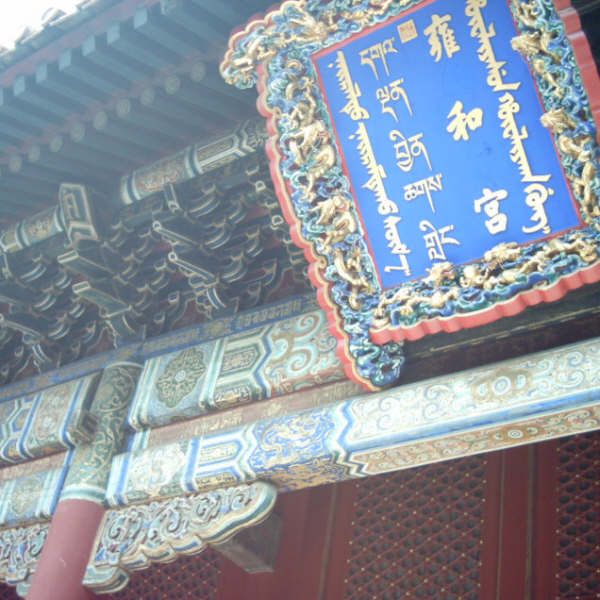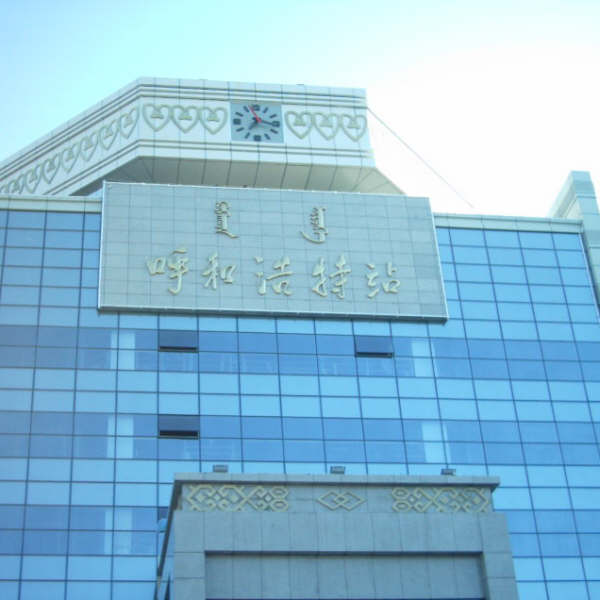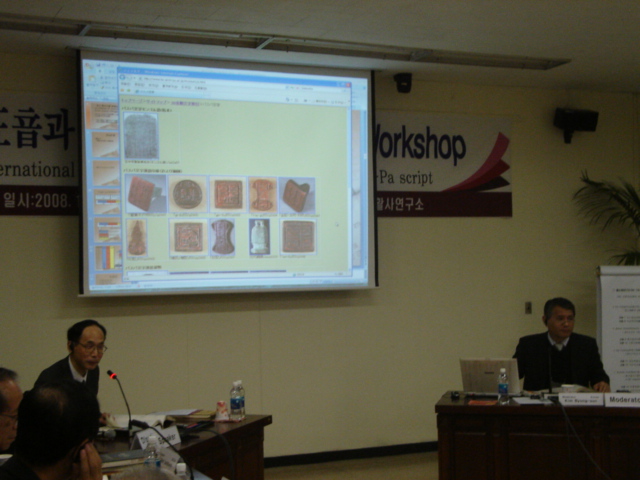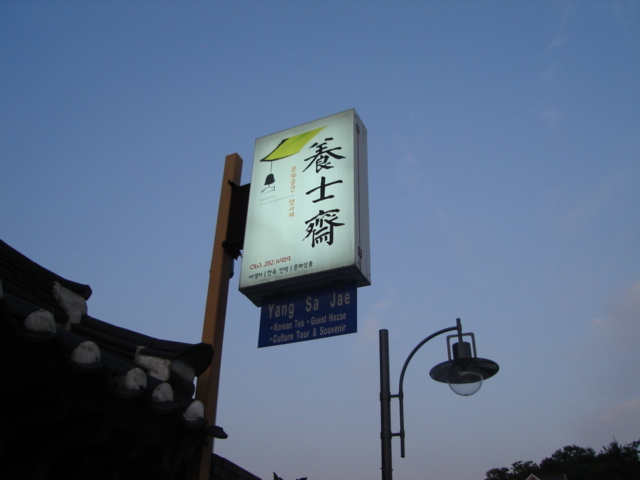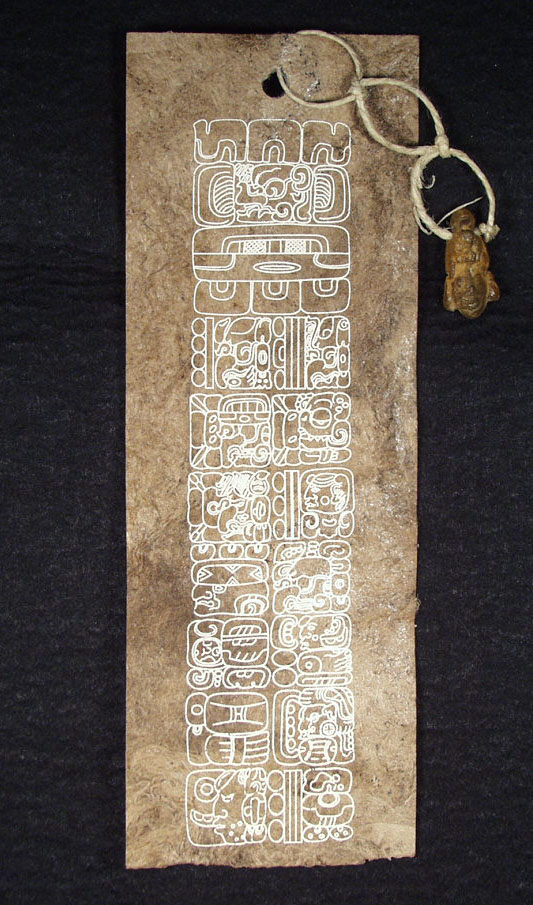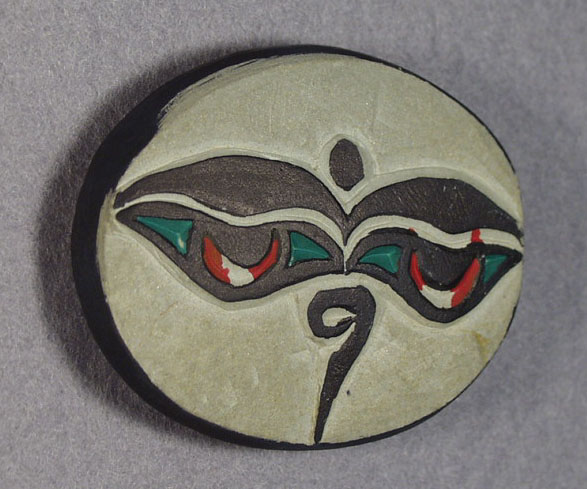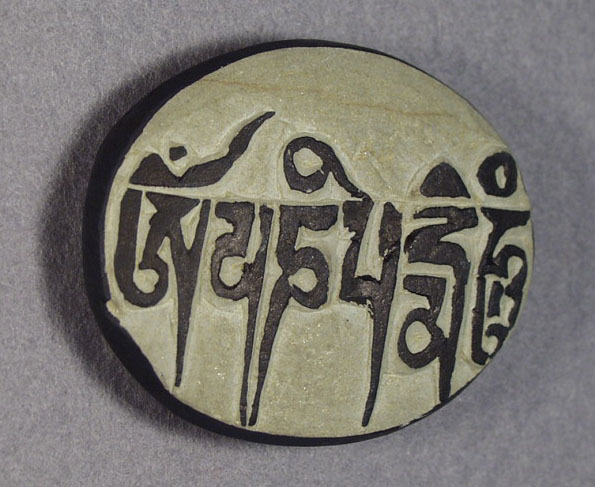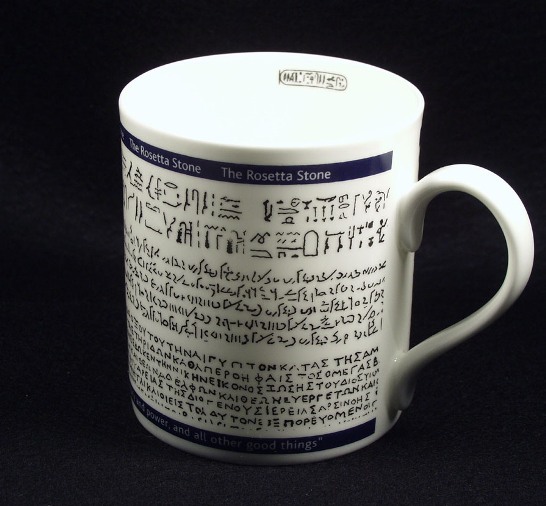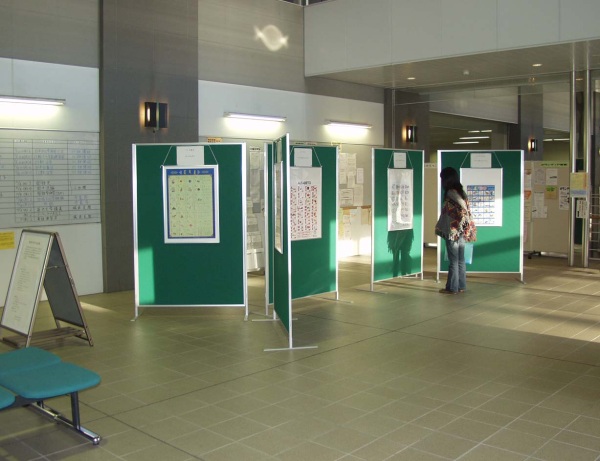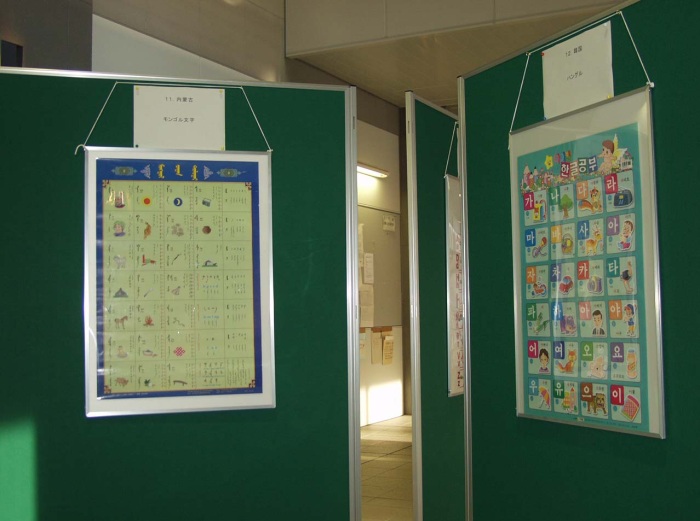
養士斎に泊まる 9月12日(土)、13日(日)の両日、韓国・全州の又石大学校で開催された「訳学書学会創立総会及び学術発表会」に出席してきた。僕としては、発表の準備よりもこの学会に『訳学書文献目録』(ソウル:博文社,2009年9月)の出版を間に合わせるまでがとにかく大変たったので、全州にたどり着いた時にはすでに燃え尽き症候群のような状態だった。この間の経緯については遠藤光暁先生の「先進国としての韓国―中国語学研究を通して見る」(『東方』346号,2009年12月)に詳しい。 会議では初代会長となられた鄭光先生(高麗大学校名誉教授)を始め韓国側の諸先生から連日歓待を受け、また研究上の交流も非常に実り多いものだったが、滞在最後の日に遠藤先生・更科慎一氏とともに「養士斎」(ヤンサジェ)という伝統的韓国住居に泊まったことがとても印象に残っているので、今回はそれを写真で紹介しよう。
→他の写真へ 養士斎は伝統的な家屋と街並が保存されている「全州韓屋村」の一角にある。詩人・朝鮮語学者として名高い李秉岐氏(1891-1968)の旧居で、氏が1950年代に全北大学校の文理大学長を務めていた時の住まいであるという。現在は民宿となり一般客も泊まれるのだそうで、今回はソウル大学校に留学中の杉山豊さんが予約を取って下さった。 朝鮮語学に明るくない僕は、最初李秉岐先生の旧居と聞いてもピンとこなかったのだが、その号が「カラム」であると聞いて、おお、あの「カラム文庫」のカラムか! と一気に気分が盛り上がった。ソウル大学校奎章閣のカラム文庫は、訳学書の所蔵機関として目録にさんざん出てきたからである。 中に入ってみると、そこかしこに見られる素朴な山里の雰囲気が「燃え尽き」の身には実に心地よかった。荷物を降ろし、皆で少し周りを散歩したあと、夕食には全州名物のビビンバを食べ、近くの伝統茶室でお茶を一服してから養士斎に戻った。 泊まったのは通常のオンドル部屋だから、当然部屋は狭く布団は薄く床は固い。加えて僕は寝つきが悪いので、いつもはラジオかCDでもつけないとなかなか眠れないのだが、この日はそんなことが全く気にならず、あたかも全身を良い「気」に包まれているような感じで深い眠りについた。 翌日は早々にソウルに向けて起たなければならなかったので、あまりゆっくりできなかったのが何とも残念で、機会があればぜひまた訪れてみたいと思っている。カラム先生にあやかって、あの良い「気」が頭の方にも効いているとよいのだけれど。 [2009.12.15 竹越孝] |
文字と意匠―(5)ロゼッタ・ストーンの文字をあしらったマグカップ 文字本来の用途から離れてデザインとして描かれた文字がある。いろいろなものがあるが、 しばらくは陶磁器に書かれた文字を見ることにしたい。 このマグカップは大英博物館で購入したものという。過日、知人より土産として当館にご 寄贈いただいた。おそらく、当サイトの“いろいろな話”をご覧のうえで、お気遣いいただいたの であろう。嬉しい限りである。
ただし、マグカップにプリントされた3種の文字が、内容において対応しているわけではない。マグカップのヒエロ グリフ(2行)は、ロゼッタ・ストーンのヒエログリフ部分の最下部の2行から採ったものである。デモティック(5行)は最上部 の5行から、ギリシア文字(6行)は最上部の6行から採ったものである。 ここで、マグカップの写真をもう一度ご覧いただきたい。カップの内側に、楕円の枠(カルトゥーシュと称す。永遠を 象徴する結んだ縄の枠)に囲まれた文字がある。これはロゼッタ・ストーンのヒエログリフ部分の最下段から採ったもので、 プトレマイオス5世の名である。ヒエログリフで刻されている。ギリシア文字ギリシア語文の方にもプトレマイオスの名は 登場する。解読者シャンポリオンは、このような固有名の対応を契機として、エジプト象形文字の解読を成功に導き、一躍 時代の寵児となったというわけである。 さて、“文字と意匠”という面から、このマグカップみた場合、どういうことになるのであろうか。マグカップの作り手は、 言うまでも無く、文字による情報伝達は意図していない。博物館の顔であるロゼッタ・ストーンの文字をあしらって来館の記念品とし、 販売促進を考えたという面はあるであろう。あるいは博物館の宣伝にもなると考えたかもしれない。 カップの利用者のほうはどうであろうか。いま、故郷の我が老母がカップを手にした図を想像しているのであるが、文字意匠 はそれほど美しいものではないから、これに関心は示さず、“落書きのない方のカップをくれろ”と心の中でつぶやくに違いない。 もっとも、最近はヒエログリフを目にする機会も少なくないから、この文字意匠によって古代エジプトを想起する方もおられる であろう。ロゼッタ・ストーンの所有国イギリスや解読者シャンポリオンの母国フランスの人々であれば、更に別の感慨を抱くの かもしれないが、そのあたりのことは確かめたことがない。しかしなんといっても、大英博物館の土産であること、ロゼッタ・ストーン を模したものであることに“関心を持っている”人の手の中で、このマグカップの文字は文字意匠としての効用を最大限に発揮す ることだけは間違いない。現にいま手の中で輝いている。 [2009.11.17 吉池孝一] |
おみやげ 先月、友人からお土産を何点か頂いた。ベルギーで開かれた学会に出席したということで、まずはオランダ語の(オランダ語による)文法書を一冊。私は学生時代にオランダ語の授業には初回に顔を出しただけで、結局履修するのをやめたため、オランダ語の知識はないが、英語とドイツ語の中間的な特徴を示している(ように見える)ので、ただ眺めていても面白い。件の友人もやはりオランダ語は話せないので、ベルギーではドイツ語を使っていたらしい。それでも相手は理解し、英語で答えた(!)ことで無事に意思の疎通がはかられた由。実はベルギーではオランダ語とフランス語以外に、ドイツ語も公用語の一つだということを後に知った。 そして、彼女がパリに立ち寄った際、チベット物産店(?)で入手したという御利益のありそうな石も頂いた。手のひらに収まるサイズのもので、これがその写真。
ついでに、と言って、去年メキシコに行った時に入手したというお土産も頂いた。マヤ文字が記された栞(?)である。 ![]() [2009.10.21 中村雅之] |
京都国立博物館の展示 先日、「シルクロード 文字を辿って」という展示を見に、館員一同で京都に行って来た。日本にいてこれだけの展示を見る機会もめったにないだろう。 今回の展示は、文字資料のみで構成されているのが大きな特徴である。従来「シルクロード」と題した展示では仏像や絵画や種々の器といったモノが中心であったが、今回は文字の記された資料100点以上を展示しており、文字に興味を持つ者にとってこの上なく楽しい展示であった。 ![]() →他の写真へ 100年以上も前に建てられたという京都国立博物館の奇妙な外観にしばし呆然として入り口の入場券売り場に行くと、やたらと大きな看板が出ていた(上の写真)。まずは構内のカフェで簡単な食事を済ませ、それから本館に入った。 今回の展示はほとんどがロシア探検隊の収集物で、展示物の配置は出土地別になっていた。順路に沿って、最初にコータン、クチャ、トルファンなどから収集したカローシュティー文字、ブラーフミー文字、ソグド文字、ウイグル文字などの写本、次に敦煌から収集した大量の漢文文献やチベット文字資料、最後にハラホト出土の西夏文字資料など、いずれも逸品ぞろいで見ていて飽きないものばかりだった。 関連展示として、京都の各地に保管されている国宝・重文級の古写本や版本も十数点あって、中でも原本『玉篇』の古写本の断簡は見応えがあった。 このような充実した文字資料の展示は、1998年に東京で開かれた「法華経とシルクロード」展(東洋哲学研究所主催)以来であろう。その際には、ロシア・東洋学研究所(サンクトペテルブルク)所蔵の仏教文献が公開され、14の言語による47点の展示があった。今回の京都の展示では、言語と文字の種類では遠く及ばないが、何と言っても140点余りの資料をそろえた点が評価できる。ちなみに、今回展示されたカローシュティー文字「法句経」は前回の東京での展示でも見た(はずの)もので、この資料の来日は2度目ということになる。 また、今回はロシア探検隊の収集物をまとめて展示したこともあって、クレメンツ、オルデンブルク、コズロフ、ペトロフスキーという、探検隊に関わった人たちの肖像や解説も備わっていて、ロシアの中央アジア学を総合的にとらえるいい機会になった。 [2009.9.16 中村雅之] |
文字と意匠―(4)“いろは”の花器 文字本来の用途から離れてデザインとして描かれた文字がある。いろいろなものがあるが、しばらくは陶磁器に書かれた文字を見ることにしたい。 これは、“いろは歌”四十七文字に“ん”を加えた48文字の“いろは”の花器である。小さな火鉢くらいの寸法で、見てのとおり、全面に筆で平仮名が書かれている。この花器(安物の信楽焼)であるが、近所の行きつけの喫茶店で購入した。実はこの喫茶店、陶磁器店も兼ねている。陳列棚に並んでいたものを見そめて購入したというわけである。しばらくの間、研究室の片隅で眠っていたが、今回無事にデビューとなった。
文字と意匠―(3)漢文の陶製枕 文字本来の用途から離れてデザインとして描かれた文字がある。いろいろなものがあるが、 しばらくは陶磁器に書かれた文字を見ることにしたい。 ![]()
群鳥冷栖霜在木 (群鳥 冷栖シ、霜 木ニ在リ) 孤?寒叫月懸山 (孤猿 寒叫シ、月 山ニ懸ル) “対聯”と呼ばれる対句である。その意味するところは“群れなす鳥が寒々と木の枝に止ま っており、その木には霜が降りている。遠く孤猿の寂しげな叫び声が聞こえる。見ると山の上 には月が懸かっている。”というところであろうか。静寂な雰囲気であることだけは確かである。 枕の作者は、“寝る前にこの対聯を見て穏やかな心持で眠りに就いてもらいたい”との願いを 込めて作ったのであろうか。或いは、よく眠れるようにとの“おまじない”であろうか。もっとも、 この手のものは、作者の意図と、日常枕を利用する人の思いが一致するとはかぎらない。あんがい、 ただの飾りとして気にも留めないというのが、ふつうの在り方なのかもしれない。 なお、広州の南越王墓博物館の一角で、さまざまな枕が収集展示されているという。機会があれば 一度のぞいてみたいと思っている。[2009.5.13 吉池孝一] |
文字と意匠―(2)ハングルのマグカップ 文字本来の用途から離れてデザインとして描かれた文字がある。いろいろなものがあるが、しばらくは陶磁器に書かれた文字を見ることにしたい。 さて、昨年のことであるが、友人宅におじゃましたおり、ハングルがあしらわれたマグカップをみた。聞くと、韓国のスターバックスで売っているという。その後、韓国に行く機会があったので、ソウル市内の、くだんのコーヒーショップで買い求めたのが、この磁器製のカップである。 ![]() この韓国語(李朝時代の言葉)を現代の市民がどれほど読めるものか、門外漢のわたしには分からないが、内容自体は周知のものなのであろう。民族の誇りともいうべきハングル創製の由来が書かれたこの文は単なる意匠ではなさそうだ、ということは想像できるのであるが、それ以上のことはなんとも言いようがない。 [2009.4.15 吉池孝一] |
文字と意匠―(1)京都弁の湯飲み茶碗 文字本来の用途から離れてデザインとして描かれた文字がある。いろいろなものがあるが、 しばらくは陶磁器に書かれた文字を見ることにしたい。なぜ陶磁器なのか、理由はない。 ![]() さて、対訳というのは或る言語を他の言語で「説明する」ということであるから、この文字群は 意匠であるとともに、情報を伝えるという文字本来の働きもじゅうぶんに示している。 陶磁器の意匠としては珍しいほうである。それは、日常品としてではなく、修学旅行の学生 や一般の旅行者を目当てに土産物として作られたためであろう。「京都弁と共通語の茶碗」、 土産として話の種になりそうである。 このようなばあい、湯飲み茶碗本体が主役なのではなく、主役は意匠の方なのであろう。 主客逆転ということであるならば、これらの文字は単なる意匠ではないかもしれない。 なお、京都弁は平仮名のみで綴られ、対応する共通語は平仮名と漢字で綴られている。方言は 漢字表記の対象にならない音声言語ということである。 [2009.3.13 吉池孝一] |
中国の民族文字資料(3) 今回は中華民族園です。中華民族園は、北京中心部の北側、環状の幹線道路・三環路を出るものの、地下鉄、バス路線では案外便利な位置にあります。すぐお隣はオリンピックセンター、園内からも「鳥の巣」やスタジアムがよく見えます。 ここは、国内の各少数民族の居住建築や展示を集めた、犬山市のリトルワールドのようなテーマパークです。さすがは中国で、テーマパークとはいえ、国内の全民族を集結させた園内は気が遠くなるほど広く、とても一日では回り切れませんでした。見ることのできた、少数民族の文字をいくつかご紹介します。 ![]() →他の写真へ 山間部に住む民族が多いためか、ほとんどのエリアが、なぜあんなところにというような急傾斜の丘の上に作られており、真夏の炎天下、延々階段を上っては下りの繰り返しでかなりの体力を必要とする園内でした。でも、国内旅行せずして、一日でいろいろな民族の文化の一端だけでも触れることができるのは(斜面の上り下りも現地疑似体験の一環?)なかなか悪くなかったと思います。あいにく行き当たりませんでしたが、指定の時間に行けば、各民族のダンスや歌の上演を楽しむこともできます。展示を見るだけでなく、歌や話で少数民族の言葉を体験できれば、暑さも少しは和らいだかもしれません。 [2009.2.13榊原真理子] |
国際ワークショップ参加記B〜蔵書閣のこと〜 今回のワークショップが行われた韓国学中央研究院の中で、ぜひとも行ってみたかったのが蔵書閣だった。ここはソウル大学校奎章閣と並び称される古典籍の所蔵機関で、いわゆる中国語学の朝鮮資料も豊富に収蔵されている。 蔵書閣のある場所を聞いてみると、ワークショップ会場のすぐ裏手だということだったので、一日目の昼食を食べてから遠藤先生はじめ数人で訪れることになった。僕は午前中最後の発表のディスカッサントということで、本当はそれが終ってすっきりした気持ちで行けるはずだったのだが、日程が押していたため午後の最初に討論を行うことになり、いま一つ気勢が上がらなかった。 蔵書閣は近代的な外見だが古風な感じもする建物で、日本の国立公文書館に似ているという印象を持った。僕は中に入っただけで満たされた気持ちになり、それ以上は期待していなかったのだが、せっかくだから何か請求してみたらどうですか、との遠藤先生のご示唆もあって、20世紀初の写本資料『你呢貴姓』を探してもらうことにした。何せ、僕は今年のゼミで数人の学生さんとともにこれを読んでいるのだ。なお、僕に司書の人とやりとりするだけの会話力はないので、折から留学中の杉山さんと野村さんが通訳を務めて下さった。 ![]() →他の写真へ ところが、コンピューターで検索しても一向に引っかからないという。司書の方があれこれ調べて下さった結果、『蔵書閣ハングル資料解題』にたどり着き、確かに所蔵されていることがわかった。「你呢」は韓国では僻字だし、何か条件に問題があるのだろうということで、司書の方は「貴姓」で引っかかるようにその場で(!)ウェブページの検索条件を変更してくれた。なお、帰国後調べてみたら、書名が『你呢責姓』で登録されていたためにヒットしなかったようだ。 現物は国家の管理だからということで見られない由。ではマイクロフィルムからの紙焼複写を請求…と思ったら複写はやっていないという。資料は画像でウェブ上に公開されており、利用者はそこからダウンロードするのだそうで、実際に冒頭の数葉分をプリントアウトしてくれた。つまり、見たい人は世界のどこからでも蔵書閣のページにアクセスして自由にダウンロードできるわけで、この情報化と開放度の高さには本当に驚かされた。 さて、帰国した翌々週、東京外国語大学で開かれた「朝鮮資料勉強会」に、『朝鮮時代漢語教科書叢刊』(中華書局)の編者である南京大学の汪維輝先生が出席され、「一種新発現的朝鮮時代漢語会話書―《騎着一匹》」という発表をされた。『騎着一匹』という奇妙なタイトルを持つ19世紀の写本資料を扱ったもので、列席者の誰もが目にしたことのない書物であるため、とりわけ大きな関心を集めたのだが、その所蔵機関は、なんと蔵書閣だという。わずか二週間前、それと気づかずに肉薄していたのか…というわけで、複雑な感慨を抱くことになった。 ところが話はこれで終らない。名古屋に帰ってから蔵書閣のウェブページをつらつら眺めていたら、『騎着一匹』はちゃんとあって、しかも全文の画像が見られるではないか! 今まで気づかなかったのはこちらの情報収集力が足りなかっただけで、一旦気づいたらすぐさま世界中の人が同じスタートラインに立てることになる。何ともすごい時代になったものだ。 [2009.2.13竹越孝] |
大原美術館の甲骨文字資料 倉敷駅前の大通りを20分ほど歩き左手に入ると大原美術館がある。門をくぐり右手を見ると土蔵のような東洋館があり、その二階に甲骨文字資料がある。十数片という小規模の展示であるが、ウイークデーは人影もまばらで資料に顔を近づけ心ゆくまで見ることができる。骨片は光沢を発し、文字もくっきりとしている。三千年以上の時を経ているとは思えないほどである。 骨片の横には伊藤道治氏による字解がふされている。(Yoshiike)[2004.10.2] |